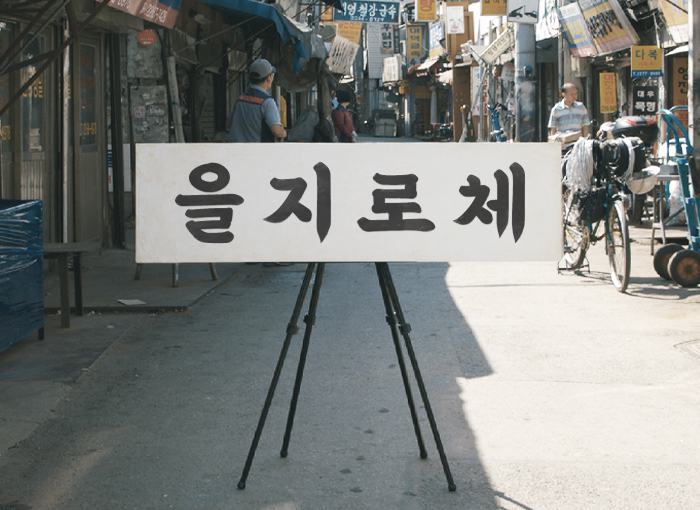
배달의민족에서 여덟 번째 서체인 을지로체를 공개했다
배달의민족에서 여덟 번째 폰트를 공개했다. 이름은 을지로체다. 역시 배민답게 이름부터 힙하다. 폰트가 출시된 직후에는 전시도 함께 열었다. 전시 장소 또한 을지로다.
이름에서 연상되듯 폰트의 특징도 을지로를 닮았다. 무명의 간판 글씨 장인이 그린 을지로 일대 가게들의 간판을 바탕으로 만들었다. 획 마다의 힘찬 시작과 페인트 붓의 여유로운 끝모양이 특징이다. 뉴트로 열풍인 요즘 사용하기 딱 어울리는 폰트다.